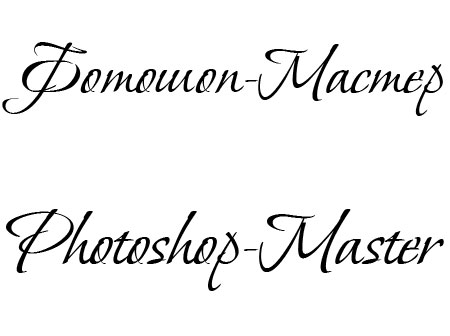
Дополнения Шрифты Татьяна Гапонова 8 июня 2009 Шрифт - Vera Crouz Интересный шрифт с поддержкой русского языка. Скачать Шрифт - Vera Crouz
Эмм...А почему вместо Ы символ Apple?
Чуть небрежно, но красиво!